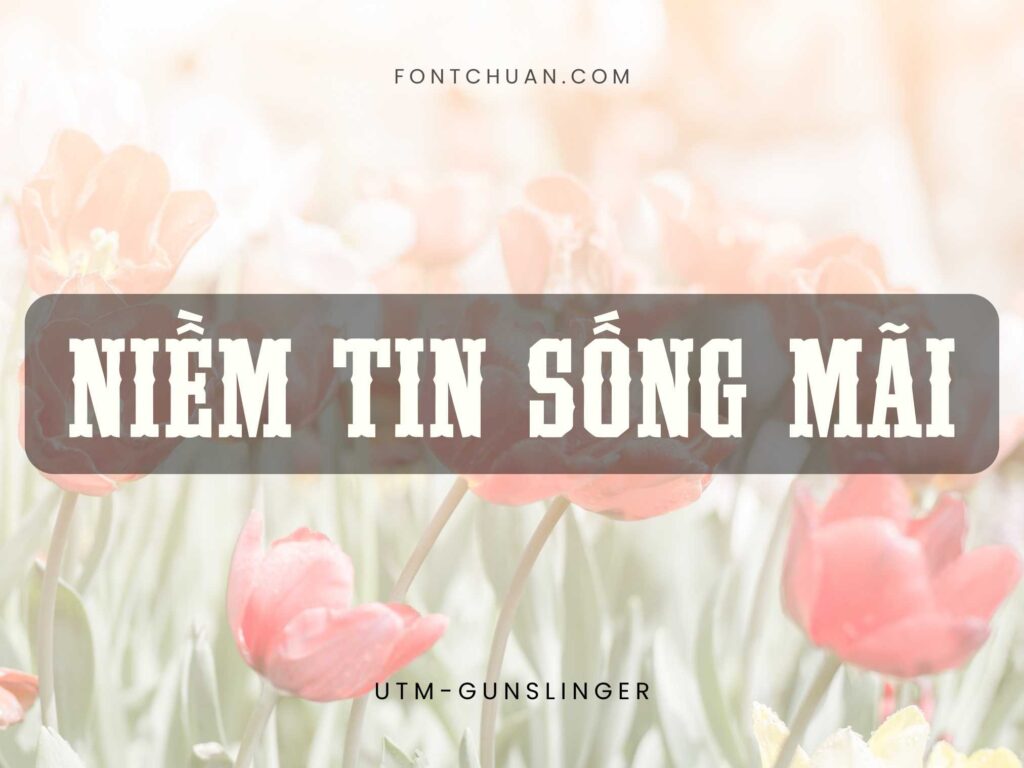
Font UTM Gunslinger Việt Hóa
UTM Gunslinger là một font chữ mang phong cách cổ điển phương Tây, đồng thời mang nét đặc trưng của Font cổ trang, lấy cảm hứng từ các thiết kế typography viền gỗ của thế kỷ 19. Font này sở hữu nét chữ mạnh mẽ, góc cạnh và đầy cá tính, thích hợp cho những thiết kế mang phong cách hoài cổ, viễn Tây hoặc các dự án cần sự ấn tượng. Font đã được Việt hóa bởi Thiên Minh, hỗ trợ đầy đủ tiếng Việt cùng hơn 200 ngôn ngữ khác, giúp mở rộng khả năng sử dụng. Thành viên của Font Chuẩn đã sưu tầm và giới thiệu font này nhằm đáp ứng nhu cầu bạn đọc, cung cấp nguồn tham khảo chất lượng và ứng dụng thực tế vào các dự án thiết kế.
Về đặc điểm thiết kế, UTM Gunslinger có các nét chữ dày, chắc chắn, với những chi tiết đặc trưng của typography vintage. Font này phù hợp với nhiều ứng dụng như thiết kế poster, bảng hiệu, bao bì sản phẩm hoặc tiêu đề trong các dự án sáng tạo. Các ngành nghề như quảng cáo, ẩm thực, thiệp cưới và công nghệ có thể tận dụng font này để tạo nên sự khác biệt và thu hút trong các ấn phẩm thiết kế